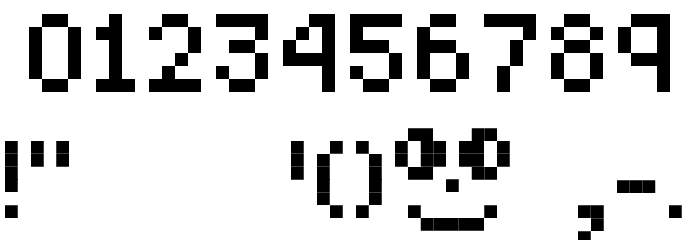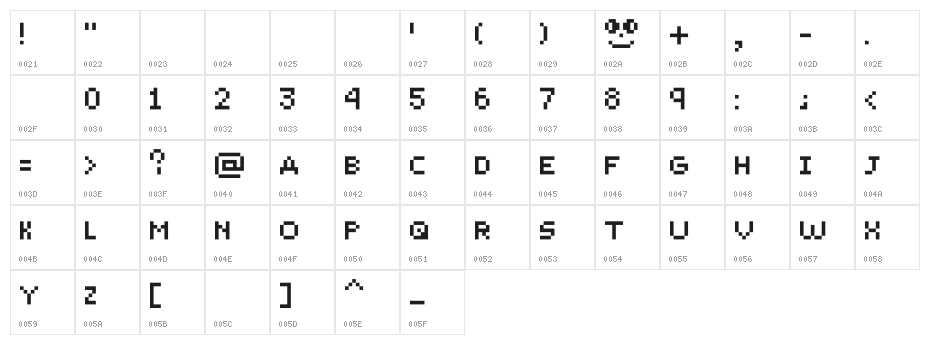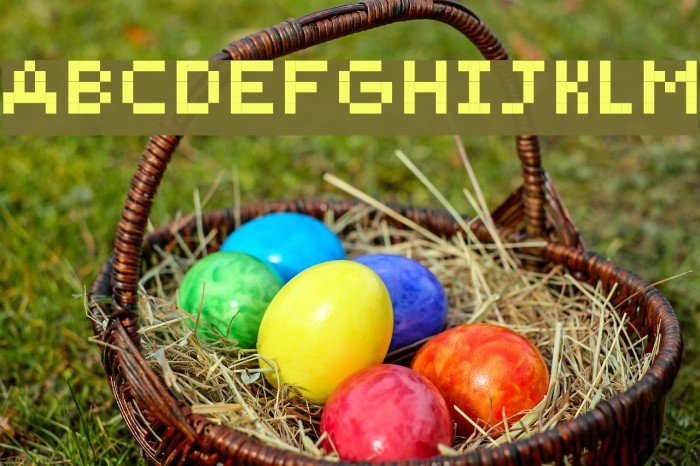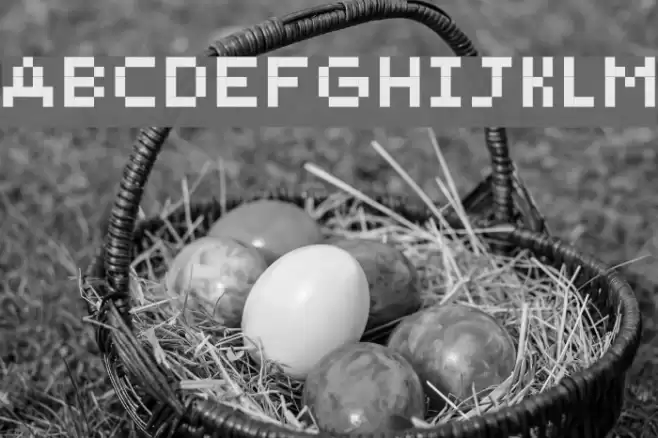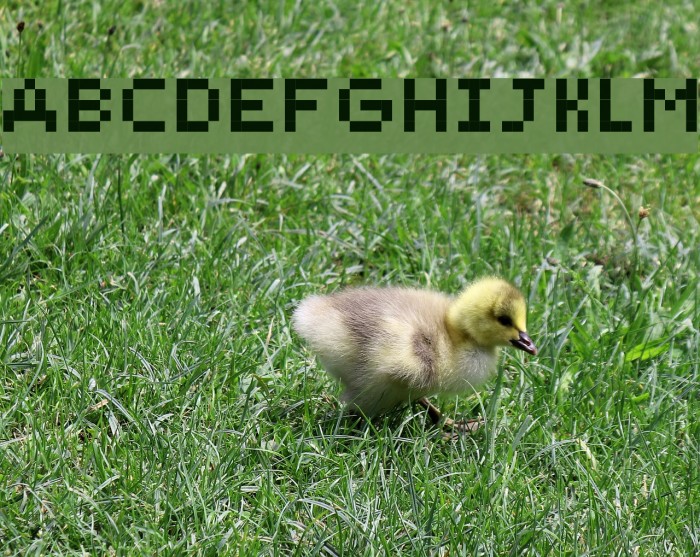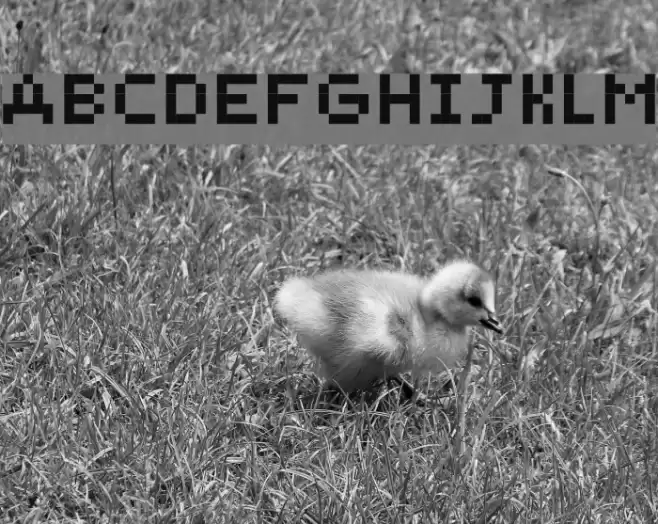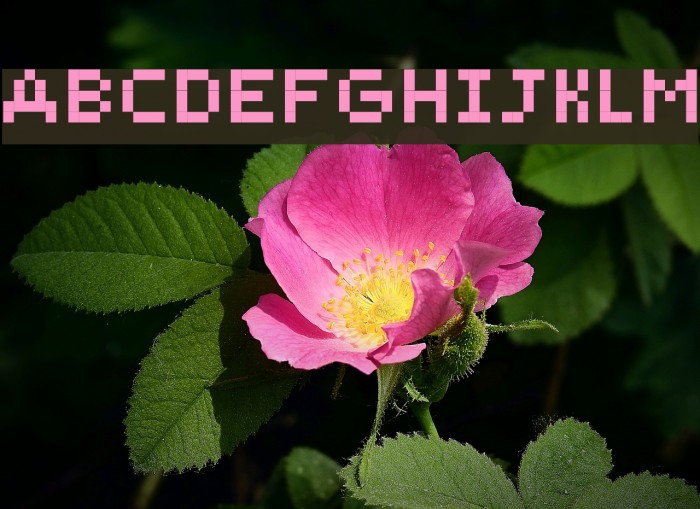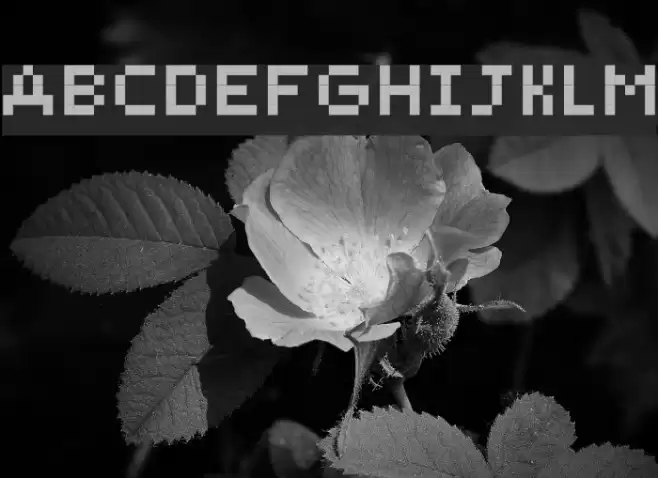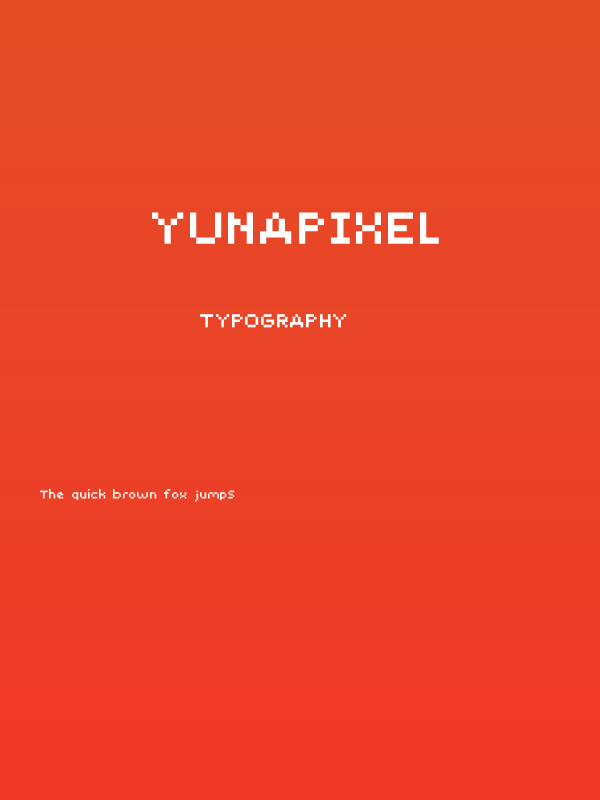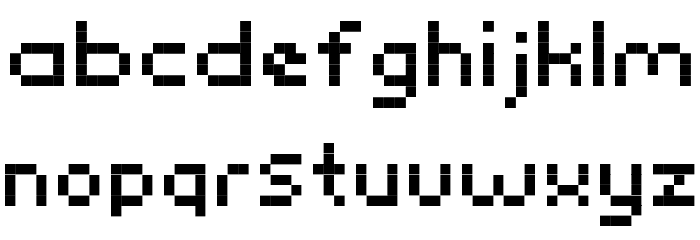
Yunapixel Font
| Caz de utilizare | Logos, Headlines, Digital Art |
| Proiecte propuse | Ideal for retro video game designs, digital art projects, and nostalgic branding. |